我看了1000张音乐banner,发现设计专辑封面有这么多技巧
除了音乐本身,不知你有没有发现它的banner,和电商的“乡村非主流”不太一样,简直是设计界的一股清流~
戳心的文案
之前网易云音乐在地铁营销事件,你一定有印象,那些抓心的文案,俘虏了一批忠实用户。
所以,有生命力的文案,一定是让banner页不普通的第一步。
逃脱方块党
你一定对那些只会中间拉方块的排版,已经累觉不爱了,而下面这些,却能让布局看起来舒适。你可以根据人物数量,选择你的排版方式。
左右
中间
上下
交错
用技巧强调内容
做ppt的时候,大家都知道,单放图片、文字,画面会很单调,所以加一些线、框来强调,增加画面秩序感。
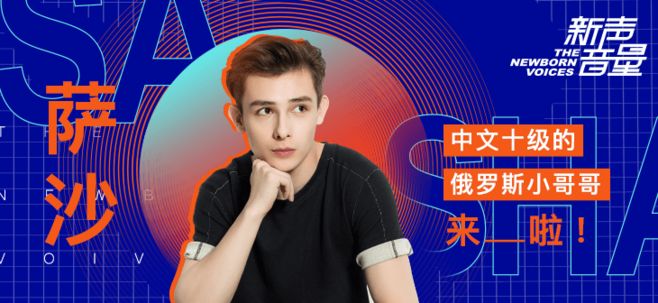
符合气质的字体
终于说到字体了,因为要符合bannner的感觉,所以它格外重要,基本没有直接用字体的,都会加各种效果。
拉长
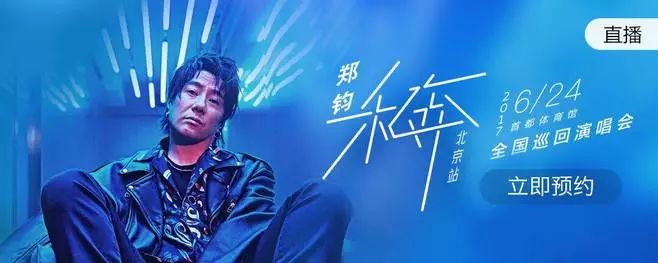
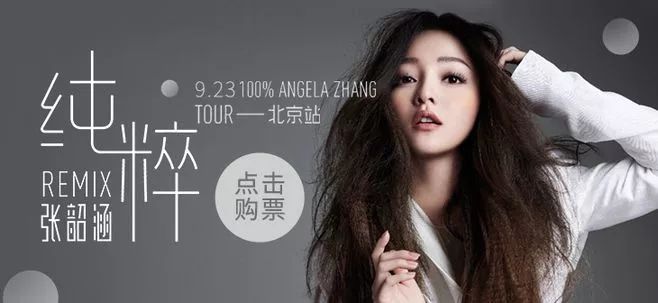
抖动
替换
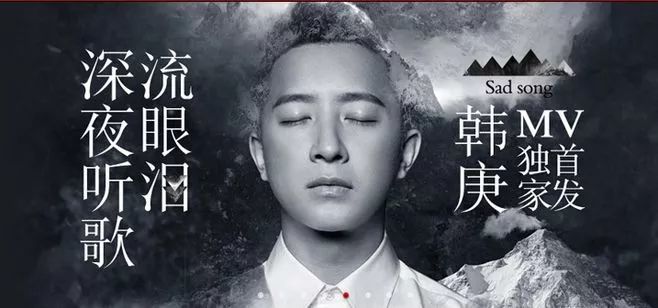
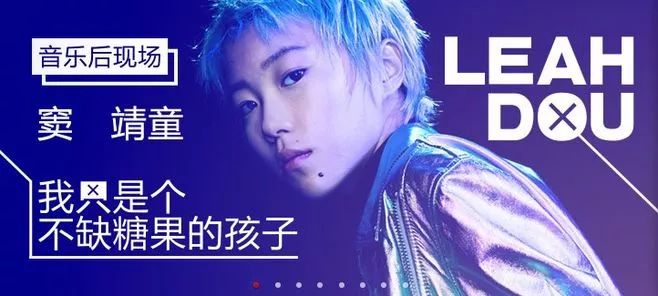
删减
增添
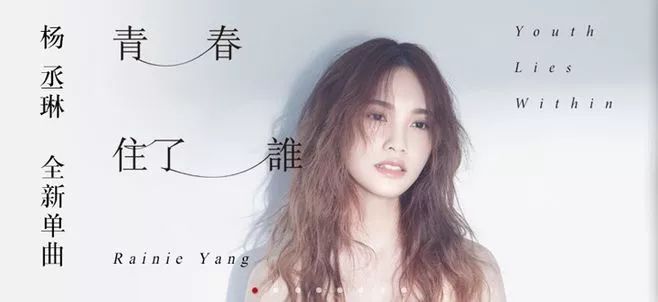
断开
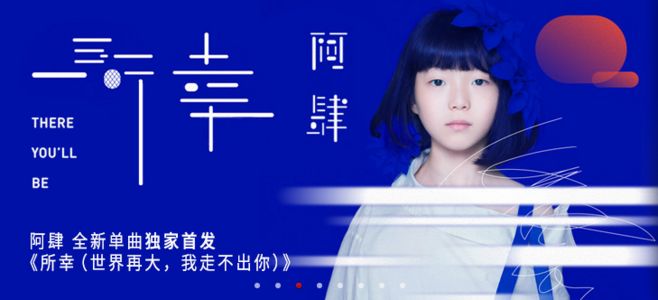
特殊
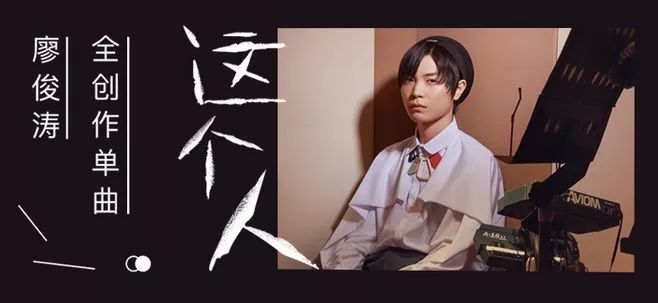
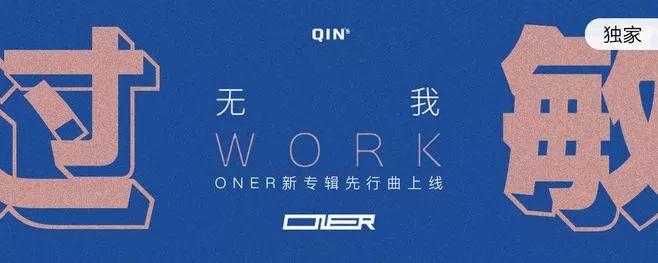
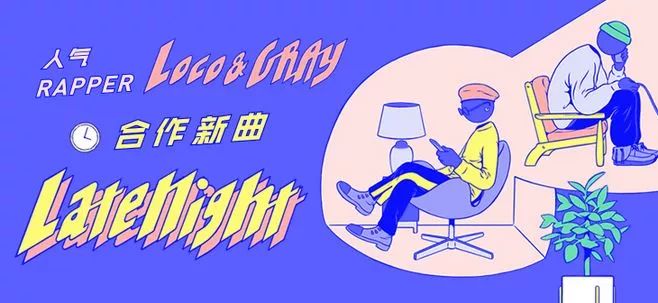
组合